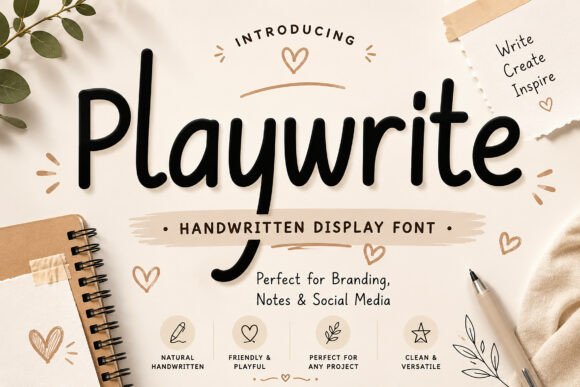
Playwrite
Se stai cercando risorse di alta qualità come Playwrite, questo pacchetto premium è una scelta fantastica per i tuoi progetti creativi.
Che tu stia creando prodotti POD (Print on Demand), partecipazioni di nozze o grafiche per i social media, Playwrite è la scelta ideale.